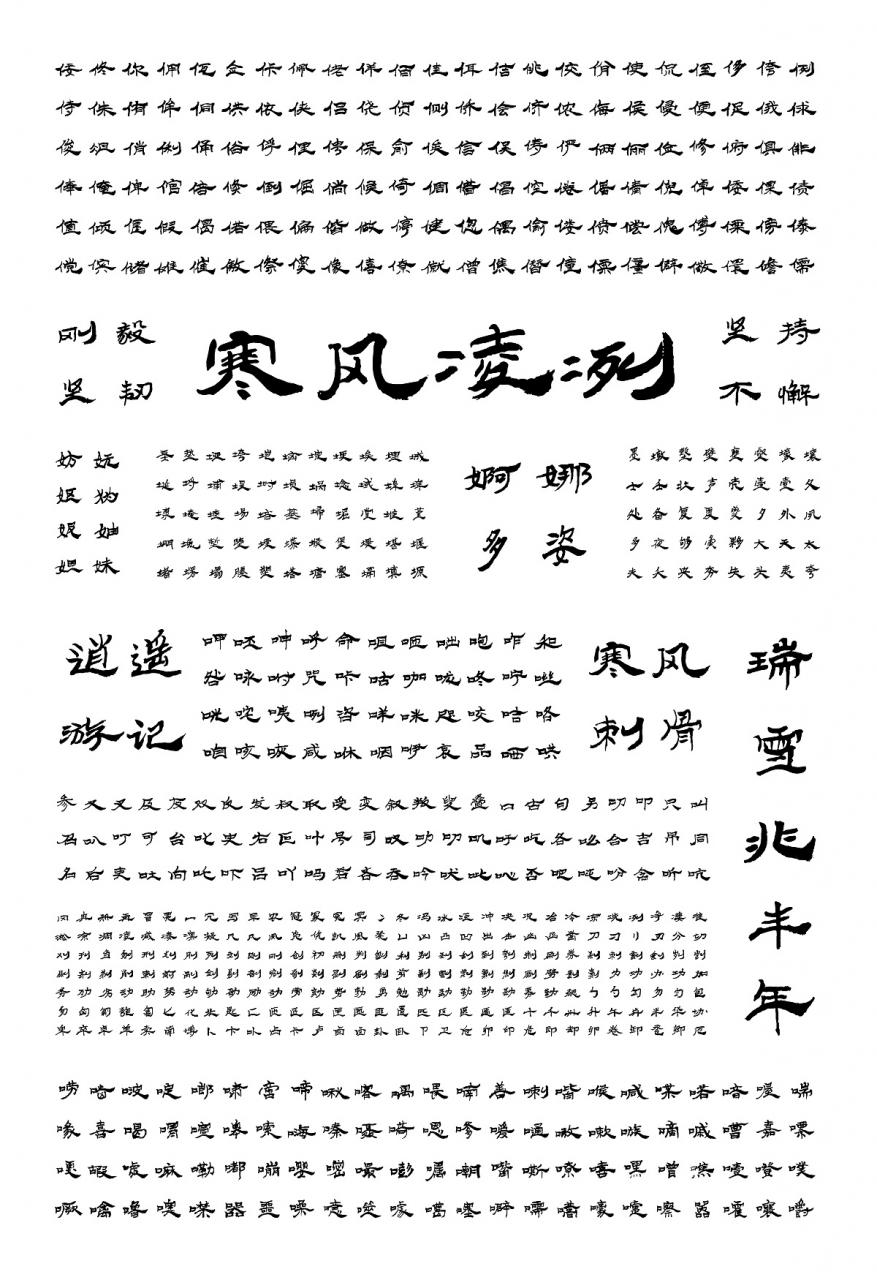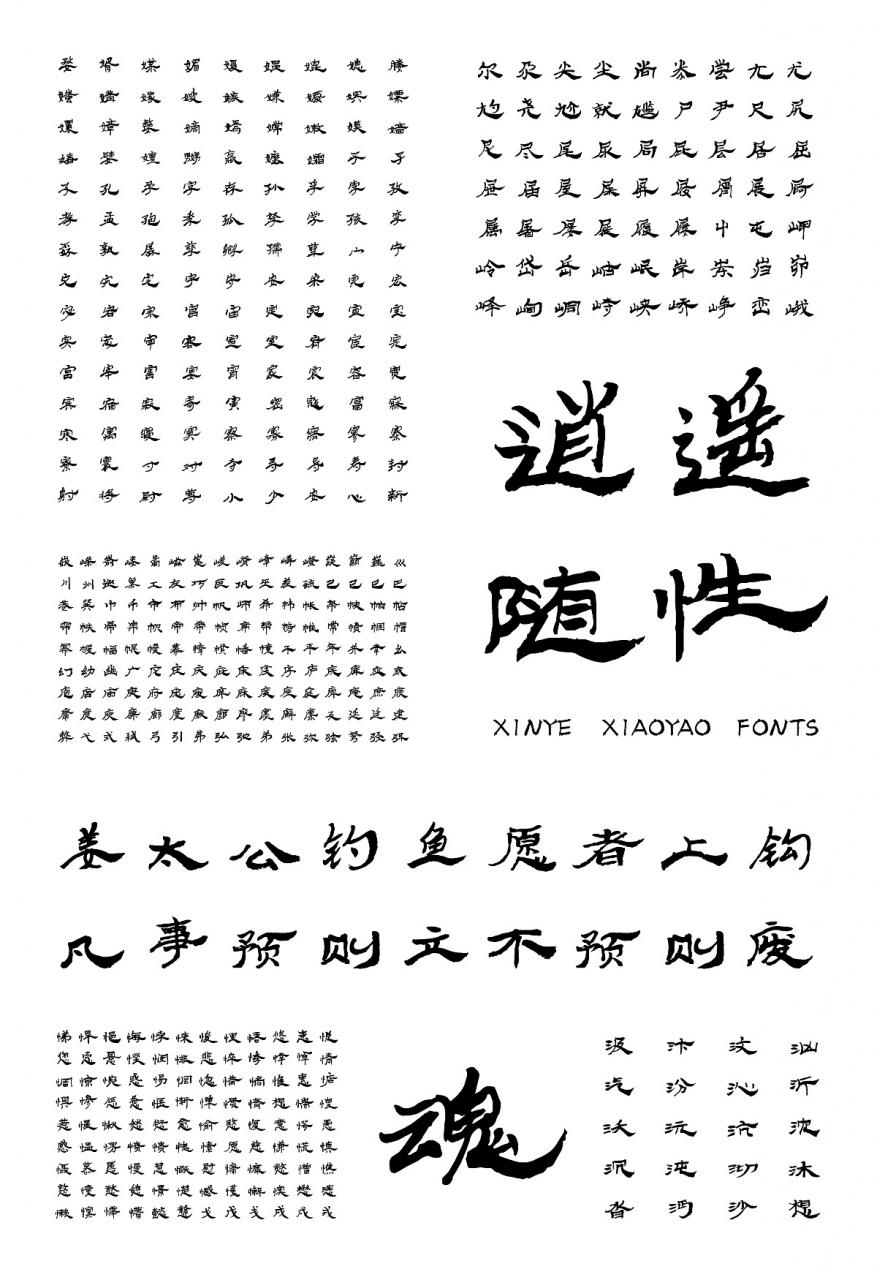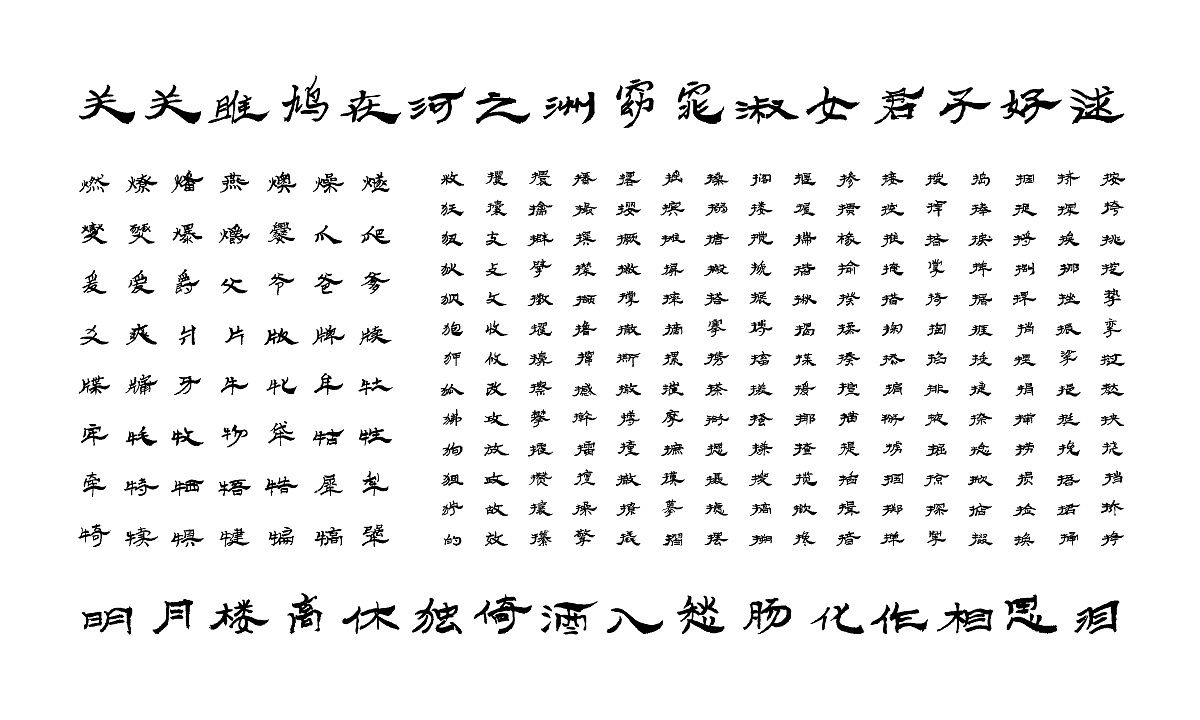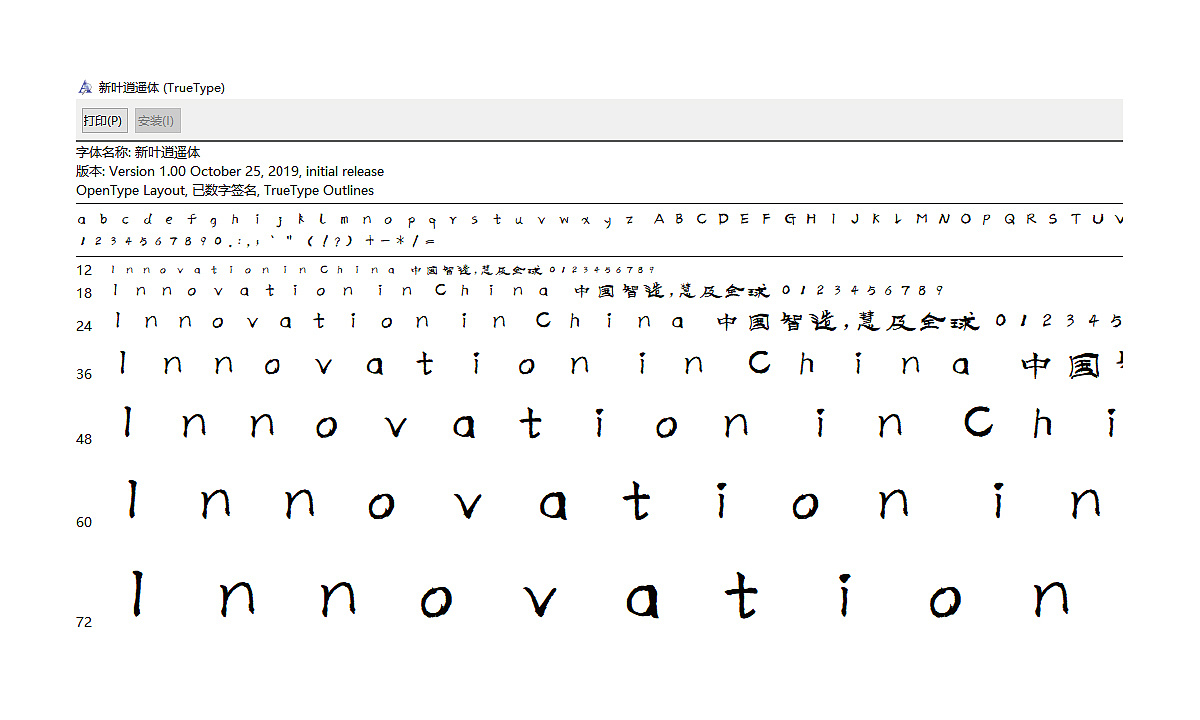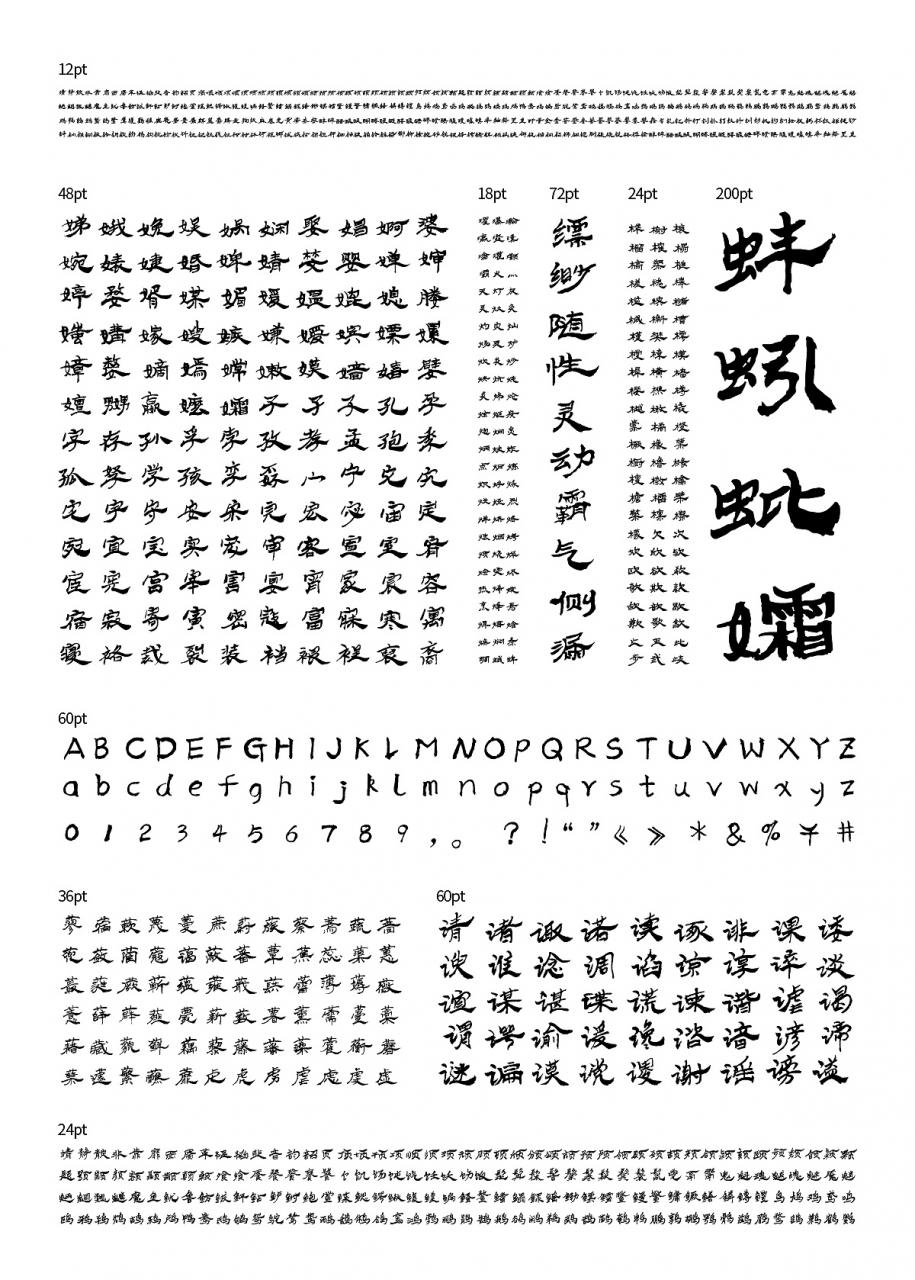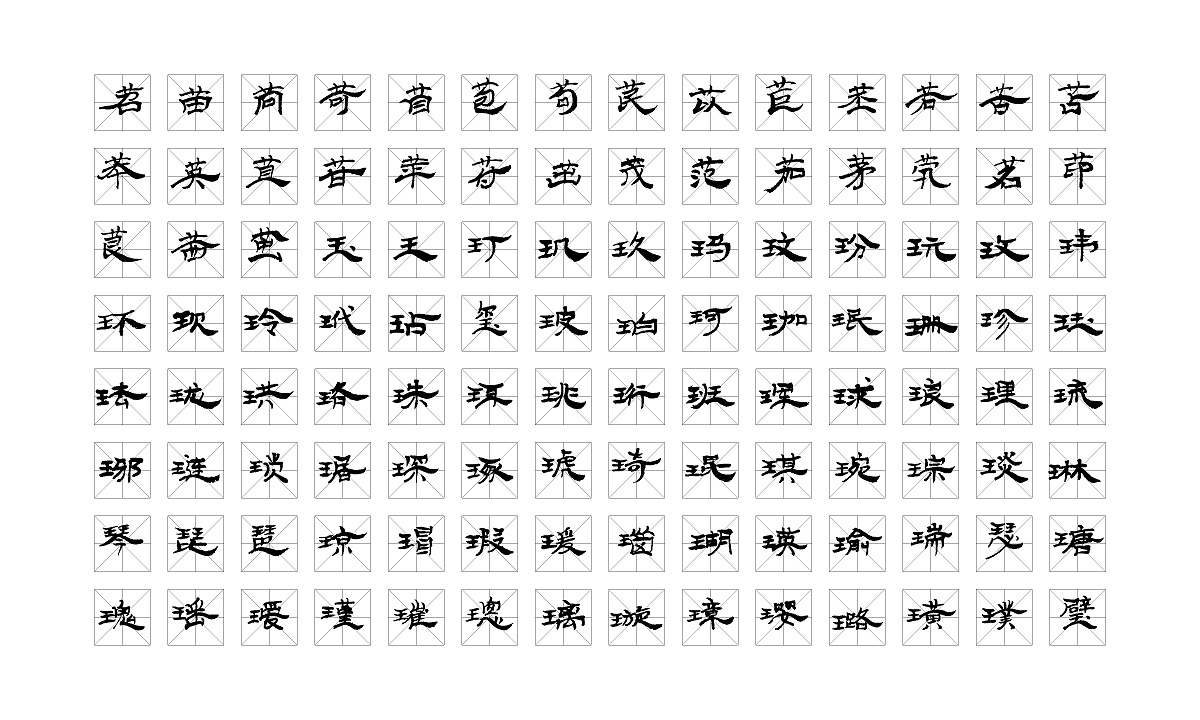
新叶逍遥体
海内皆知己,天涯尽芳草。伴君同苦乐,风雨任逍遥。逍遥自古以来就是人们吟咏的对象,每个人都希望潇潇洒洒的过一生,无论是古代还是现代。逍遥代表着一种洒脱的生命意境,代表着一个乐观的人生态度。我们期待着每个人都能以他喜欢的方式潇洒的过一生,这就是我们创造逍遥体的愿景。
被困在高楼寰宇里工作,你有多久没有好好看看外面的天空了,你有多久没有咻一咻路边的花香了。也许你会想逍遥离你很远,可是当你遇到逍遥体之后,你就会惊喜的发现,这个字体是放在文字上的逍遥。当你看到新叶逍遥体的时候,看着它一笔一画的横成飘逸,缥缈随性,你心里突然蹦出扶摇而上九万里的字句,你的心都开始跟着飘摇起来了。这就是逍遥体的魅力,让你发现原来大厦高楼里,也存在你喜欢的逍遥人生。
字体名称:新叶逍遥体
字库字数:简体+符号共计7123字
字库字体展示效果01
字库字体展示效果02
字库字体展示效果03
字体字号展示效果
字体风格细节展示效果